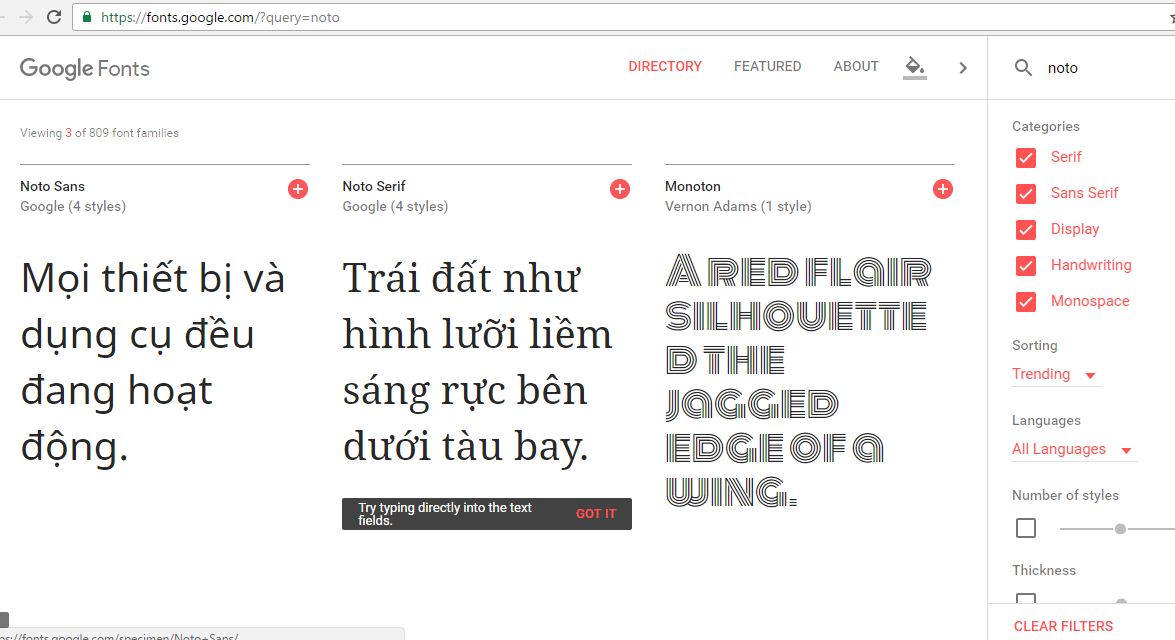
Giới thiệu về Font Noto
Theo đó , khi ra bộ font siêu phẩm này google cũng liệt kê ra những người hợp tác cùng thiết kế với họ như các chuyên gia đến từ Monotype và Adobe . Bộ font chữ này đã phải mất đến 5 năm mới có thể trình “làng” được , mục đích của google khi ra mắt bộ font này đó chính là giúp mọi người trên thế giới dễ tiếp cận được thông tin chính ngôn ngữ mẹ đẻ của mình thông qua văn bản.
Được đặt với cái tên Noto ( No more tofu ) – Nghĩa của nó là ” không còn đậu phụ nữa ” . Nếu mà đọc ra tiếng việt thì sẽ không có nghĩa , nhưng ý nghĩa của từ noto này có hàm ý chỉ bộ font này sẽ loại bỏ các kí từ ⯐ ra khỏi website.
tofu : Đậu phụ ( Chỉ những kí tự hiển thị hình ô vuông trắng trong website )